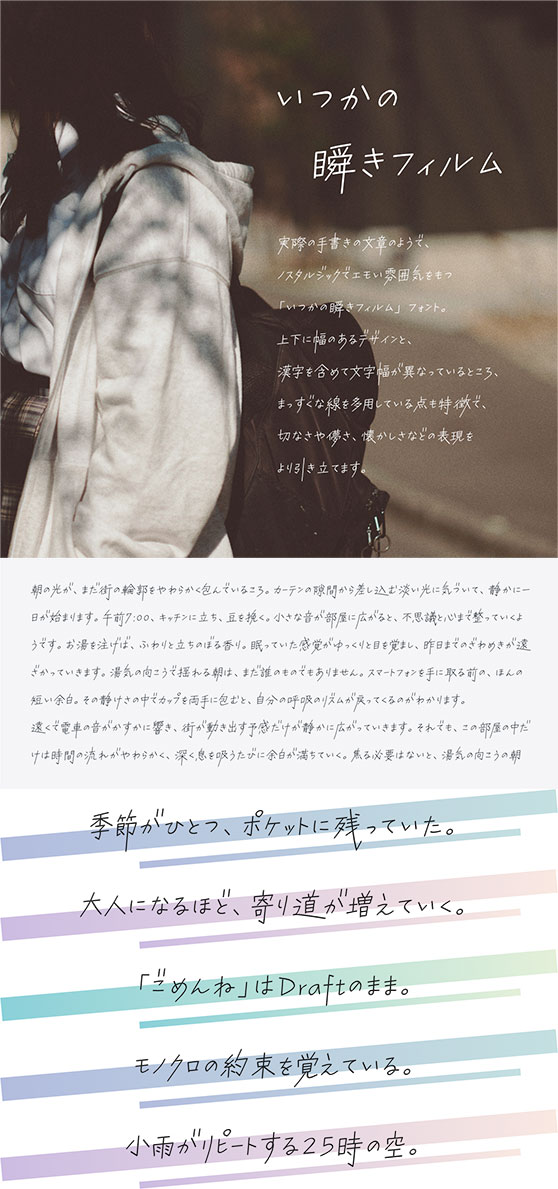
いつかの瞬きフィルム Kw-N
ノスタルジックでエモい雰囲気を持つフォントです。まっすぐな線を多用している点も特徴で、切なさや儚さ、懐かしさなどの表現をより引き立てます。コトノハワークスの手書き風フォント第2弾です。
通常のフォントより上下に飛び出しているデザインのため、ご利用のアプリによっては見切れる場合があります。 漢字の幅も一定ではないため、一部アプリでは正常に動作しません。縦書きには対応しておりません。